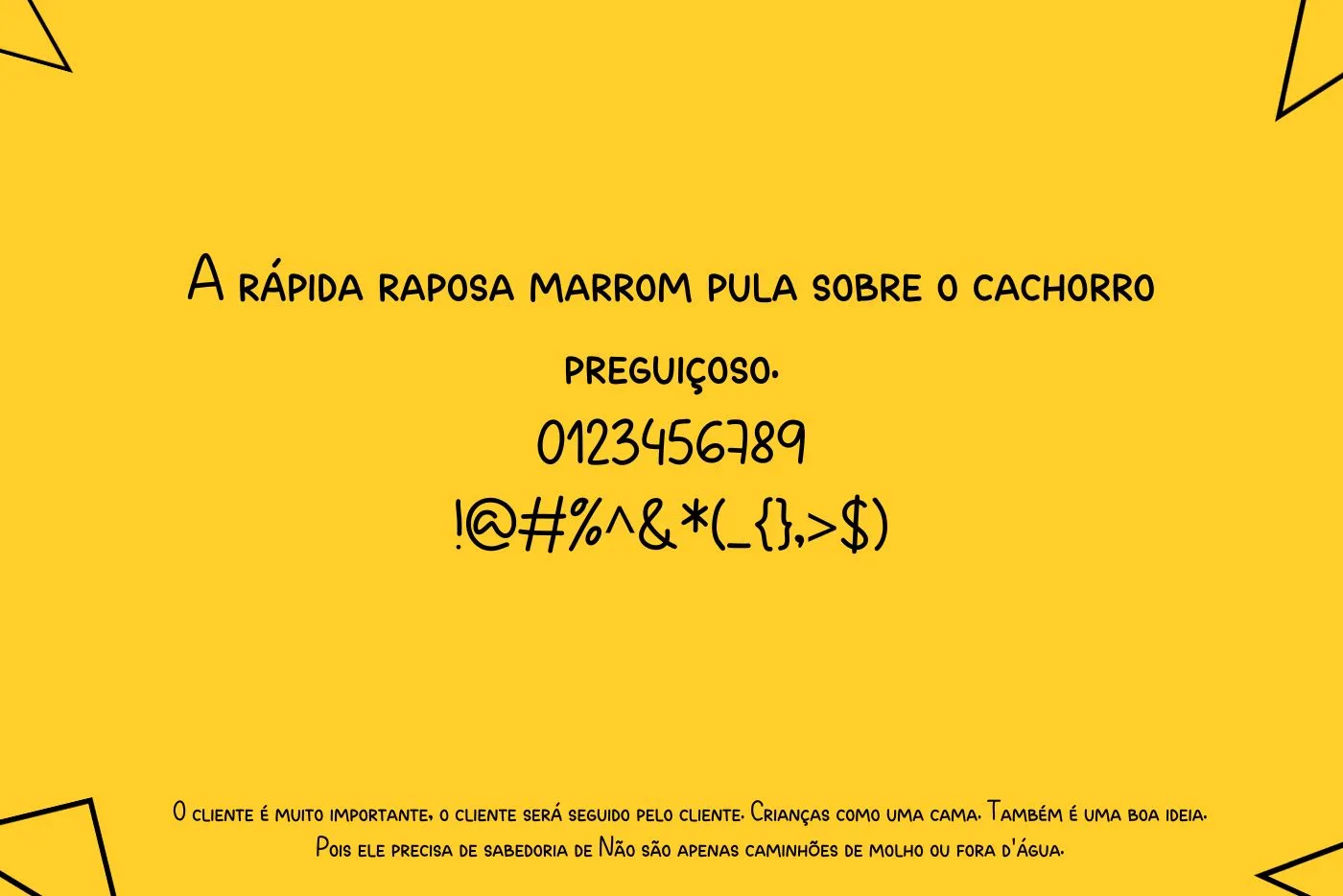
Fonte Doodly é uma fonte manuscrita. Foi desenhado por Lauritta Ivanova e publicado pela Luxfont. É uma tipografia encantadora que capta o encanto e a espontaneidade do desenho à mão livre. É amplamente apreciado por designers e criativos que desejam adicionar um toque de autenticidade e diversão aos seus projetos de design.
Cada personagem parece ter sido desenhado à mão com traços leves e despretensiosos, evocando a sensação de um caderno de desenho cheio de rabiscos criativos. Isso o torna uma escolha popular para projetos que buscam uma estética informal e única. Essa textura de aparência moderna também é ótima para combinar com fontes semelhantes, como a fonte Baloo, para fins de design avançado. Também é ótimo para fins de impressão em tecido.
Oferece uma ampla gama de estilos e personagens alternativos, permitindo aos designers personalizar suas composições tipográficas de acordo com o estilo único de cada projeto. Sua versatilidade o torna uma escolha prática em uma variedade de aplicações criativas.
Emparelhamento Com a Fonte Doodly
Combiná-lo com outra tipografia pode criar composições visuais interessantes e equilibradas. Aqui estão sugestões de emparelhamento que funcionam bem com ele:
- Uma fonte serifada clássica, como a Times New Roman, pode criar um contraste interessante com sua informalidade.
- Para um estilo totalmente manuscrito, você pode combiná-lo com outra fonte manuscrita, como a Pacifico Font.
- Se você deseja criar um design criativo e eclético, considere combinar a fonte Doodly com uma fonte decorativa, como a fonte Great Vibes.
Melhores Usos da Fonte Doodly
As melhores e mais utilizadas aplicações desta fonte são:
- Logos e marcas de luxo.
- Títulos em materiais impressos e digitais.
- Design de moda e etiquetas de produtos.
- Convites e papelaria elegante.
- Campanhas publicitárias glamorosas.
- Posts e conteúdo de mídia social marcante.
- Embalagens de produtos de alta qualidade.
- Letreiros e placas em estabelecimentos comerciais.
- Criação de arte tipográfica personalizada.
- Títulos de matérias em revistas e livros.
Qual é a fonte Doodly?
É uma fonte manuscrita. Foi desenhado por Lauritta Ivanova e publicado pela Luxfont.
Qual par de fontes oferece o melhor resultado quando combinado com a fonte Doodly?
O emparelhamento ajuda o designer a criar designs elegantes. Esta fonte pode ser combinada com a fonte Lavanderia Sturdy para dar aos designs uma aparência clássica.
A fonte Doodly é adequada para fins de exibição?
É adequado para fins de exibição, como logotipos, manchetes e títulos. Você pode usá-lo no Canva e no Adobe Photoshop para criar esses projetos.